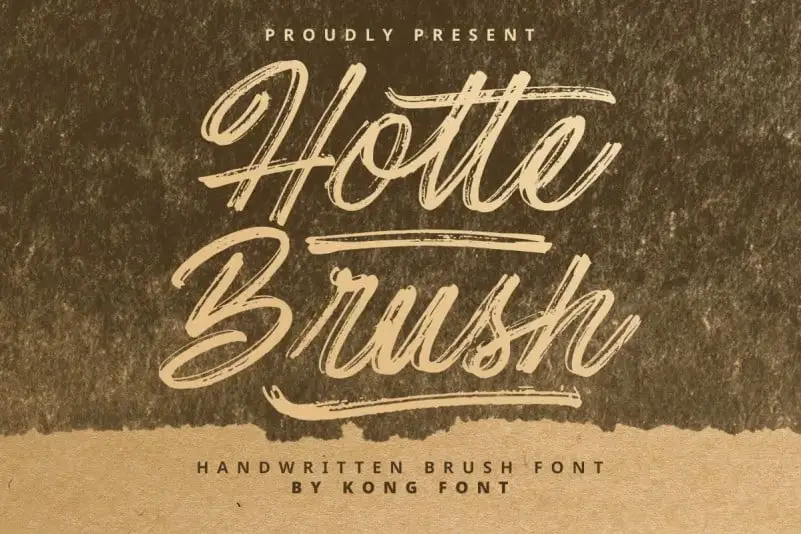
Hotte Brush Font – Download Grátis
A fonte ‘Hotte Brush Font’ é perfeita para aqueles que desejam dar um toque casual e único a seus projetos digitais. Desenvolvida pelo Designer 99designs, esta fonte de estilo brush vem com uma variedade imensa de letras, tornando-a ideal para uso em designs de títulos como etiquetas, cartões de convite, livros de títulos, material de embalagens, carteiras, cards de agradecimento, camisetas, logotipos e até mesmo cartazes. Com um aspecto casual e distante, o Hotte Brush Font é ideal para aqueles que desejam dar aos seus designs uma aparência realista e autêntica. A fonte encaixa-se perfeitamente tanto no mundo da design gráfico quanto na criação de materiais publicitários e marketing digital. Não importa qual tipo de trabalho você está desenvolvendo, a ‘Hotte Brush Font’ é certamente uma opção ótima para criar um visual único que destaca sua marca ou projeto.